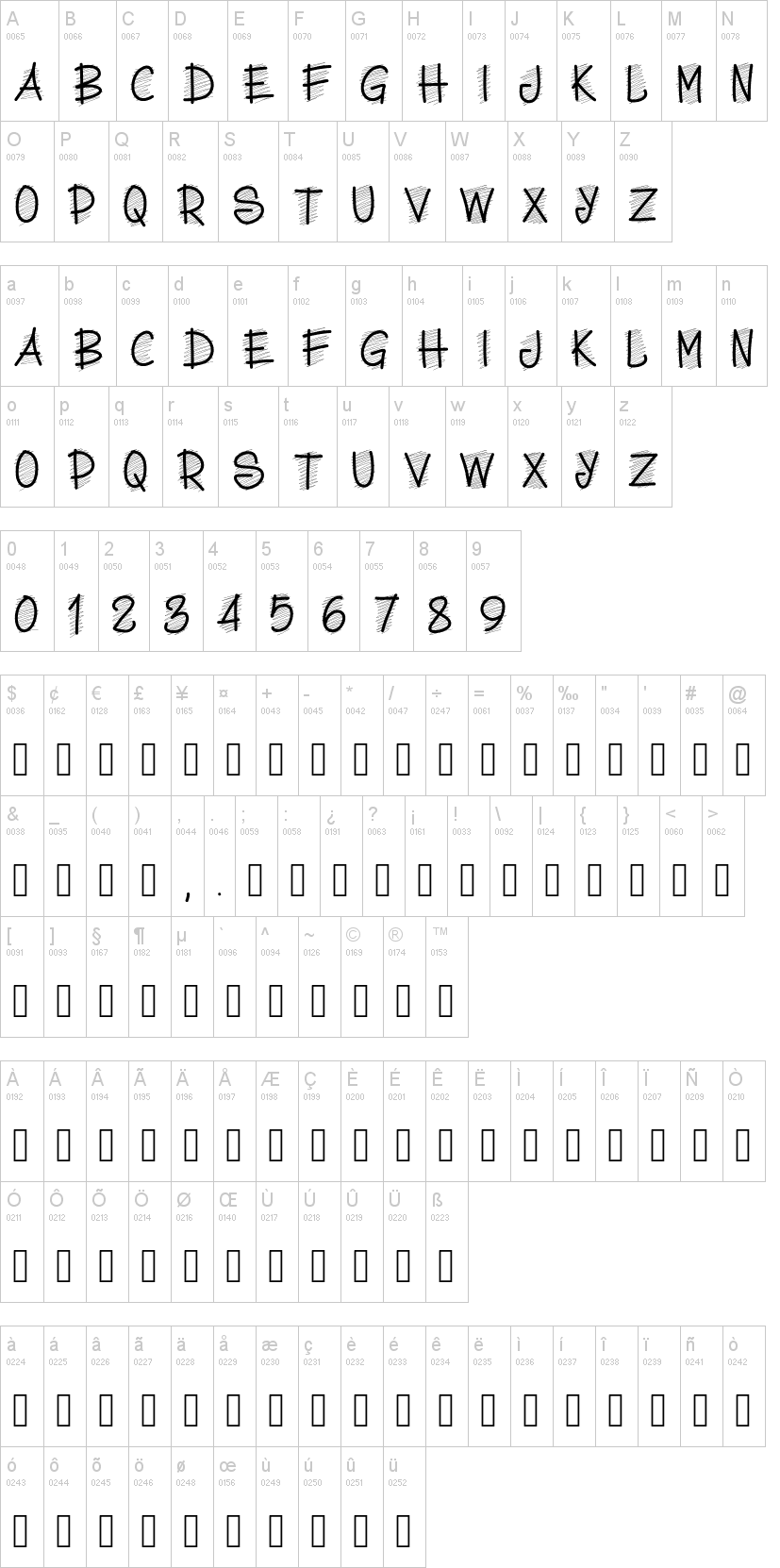
PW Scritch 是一款具有独特设计风格的字体,它具有粗犷、粗体的外观,可以为印刷品和网页设计提供强烈的视觉效果。它的字体特征包括深沉的基线,夸张的笔画,以及抽象的字形结构,这些特点使它可以用于各种不同的应用场景,从标题到标签,从报纸到网站,都能让你的设计看起来独一无二。内容介绍
PW Scritch是一款非常不错的手写艺术字体,具有很好的视觉感,适合于文化类的宣传设计、商业类品牌的广告和产品包装设计以及个性化文字排版等较多场景。